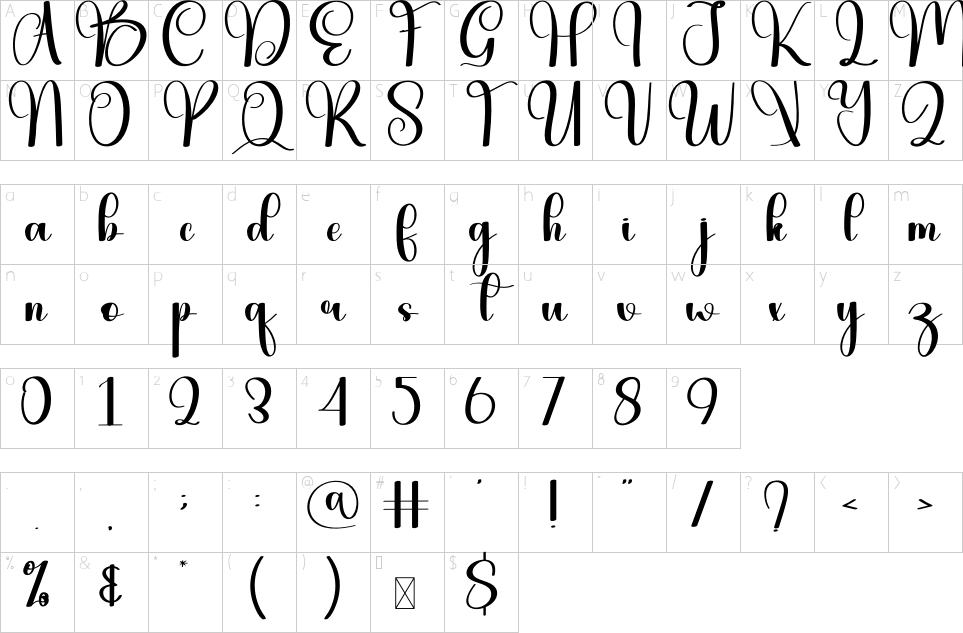
A fonte Magic Font é uma opção gratuita e divertida para designers e criativos de todos os níveis. Ela foi projetada por William Jhordy e já foi baixada 376 vezes. Com seus traços fluidos e criativos, Magic Font é perfeita para criar designs que se destacam. Baixe já essa fonte de qualidade para Windows e Mac, e inspire-se com suas opções divertidas e versáteis. Sem custos e repleta de estilo, a Magic Font é um excelente recurso para aqueles que buscam adicionar um toque único a seus projetos.